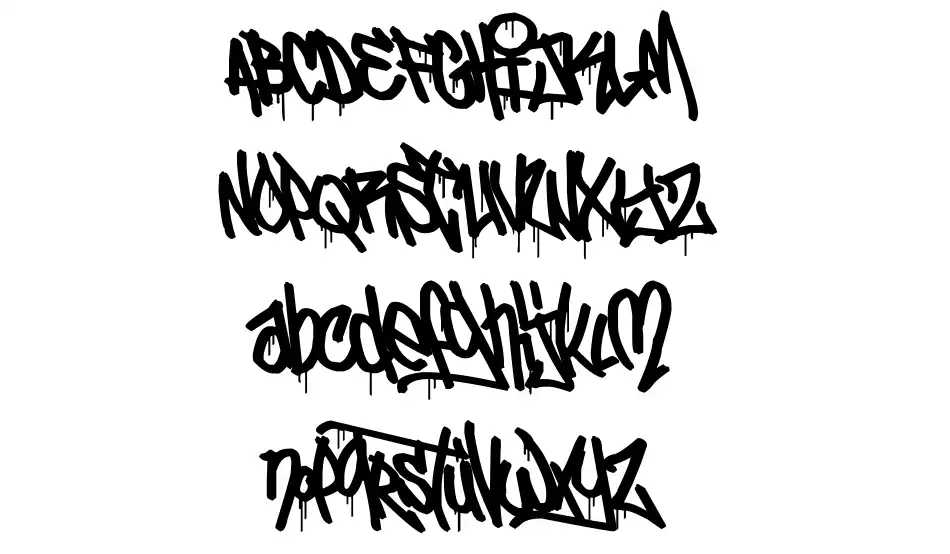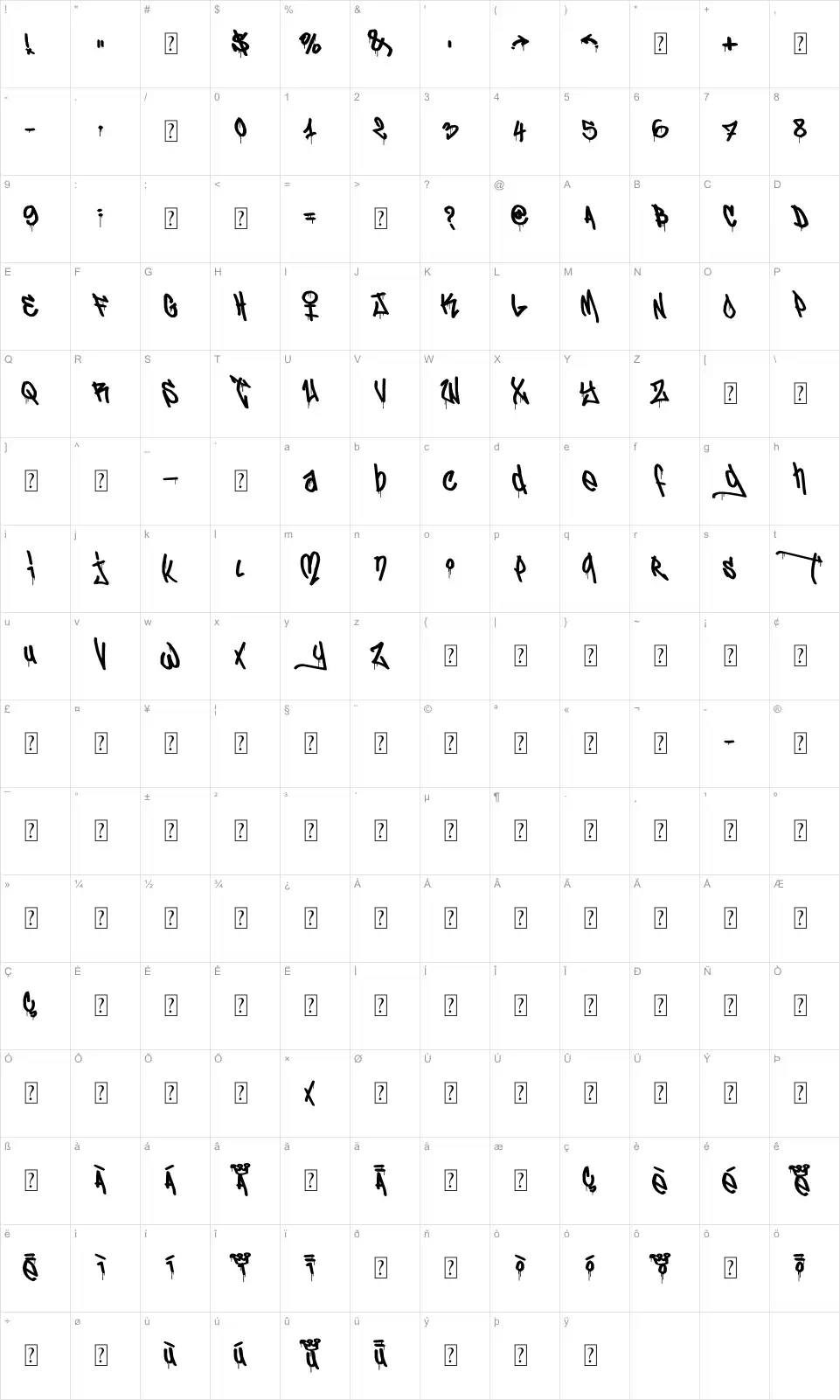
A fonte El&Font Urban CalIigraphy, criada pelo designer Jérôme Delage, é perfeita para aqueles que desejam dar um toque único e urbano a seus projetos de design. Esta fonte Script, classificada como Graffiti, traz um estilo expressivo e versátil, que combina facilmente com criações digitais urbanas. Se você está à procura dessa fonte ou simplesmente quer testá-la antes de usar, o download é fácil e pode ser feito online. É um formato TTF, o que significa que você pode usá-la em diversos programas de design. Desde sua criação em 12 de julho de 2022, a fonte já recebeu 10.325 downloads, demonstrando sua popularidade e qualidade. Com um tamanho de 21 KB, El&Font Urban CalIigraphy é uma fonte leve e prazerosa para usar, que adicionará um toque único a qualquer projeto.
Categoria: Script › Graffiti
Designer: Jérôme Delage